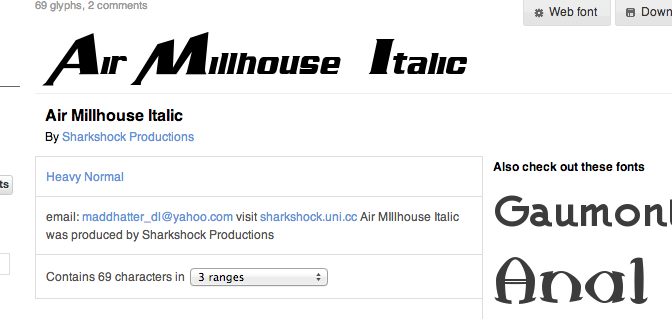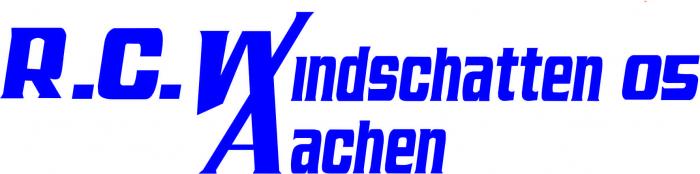
Welche Schrift könnte das sein? Habe sie nur in Kurven.
post-24810-0-56888500-1392140827_thumb.jIch habe vor Jahren dieses Logo für einen Radsportverein gemacht. Man wollte das W mit dem A verbunden haben, darum hatte ich in Kurven umgewandelt. Jetzt kann ich beim besten Willen nicht mehr sagen, welche Schrift das war. Vielleicht kann mir hier jemand helfen?
Sorry, aber ohne eine Abbildung wird es nicht gehen. Einige sind hier zwar in Besitz einer dieser hervorragenden Kristalkugeln der Marke Merlin 2000, aber auch die gibt ohne das Bild nichts heraus.
Ich meine mich aber nur daran zu erinnern, das wie gesagt, das W mit dem A verbunden wurde und ansonsten alles normal? Aber erst mal vielen Dank, auch an den Admin für das Einfügen des Beispielbildes. Werde mir die Serpentinen jetzt mal genauer betrachten. ;-)
naja, so wirklich sind es beide nicht. eventuell ist es was kostenloses was auf den beiden basiert.
ich würde eh ein redesign empfehlen, ohne verzerrte schriften, dann kannst du mit einer von den beiden nochmal sauber bei 0 anfangen ;)
Habe jetzt auch gesehen, dass es nicht identisch ist. Aber die wollen nur auf der Hose (auf'm Po) den Schriftzug Aachen in der gleichen Schrift. Dafür geht's. Nochmal danke. LG Lisa
Hi ich habe ein paar buchstaben gefunden und würde gerne wissen wie die schrift art heißt
fals es überhaupt eine ist.
oder fals es verschiedene sind eine davon würde mir schon voll ausreichen
da ich gerne meinen namen (Lox) so in Steam schreiben möchte.
Es ist die Air Millhouse!!!Danke Danke Danke.